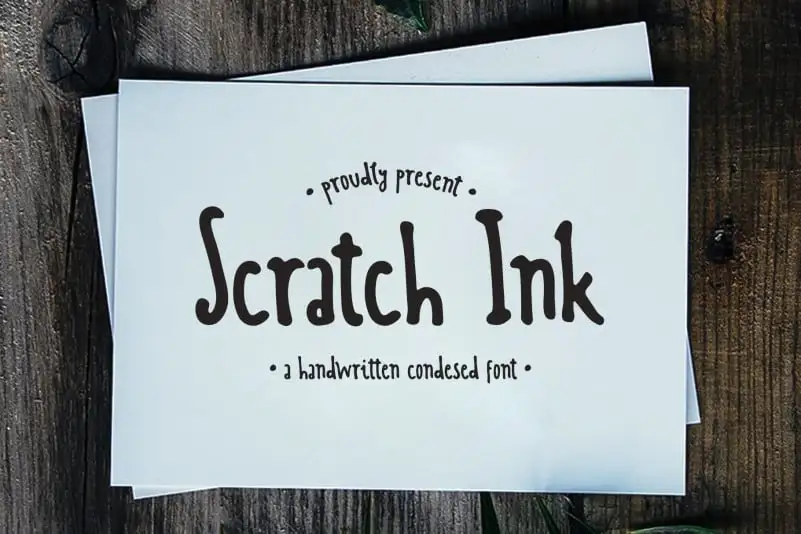
Scratch Ink – A Handwritten Condesed Font – Download Grátis
Scratch Ink é uma elegante fonte escrita a mão condensada que oferece uma aparição esparsa e limpa, perfeita para trabalhos criativos como cartas e convites de festa. Este tipo sem serif apresenta um aspecto divertido em variados ambientes, desde capas de livros até cartões personalizados. Suave e versátil, Scratch Ink se assemelha a uma tipografia sans-serif, mas oferece a riqueza do estilo pessoal do escritor ao condensar cada caractere num formato compacto e arredondado. Seja você um designer de gráficos ou um amante de estilos manuscritos, Scratch Ink é perfeito para complementar outros tipos de fontes sem deixar de ser único em sua simplicidade e elegância.
Designer: wellscriptstudio